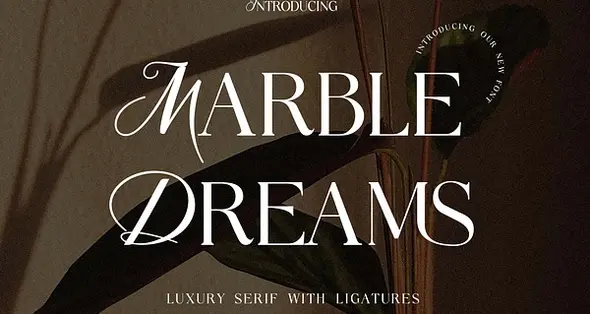
• Marble Dreams Luxury Serif Font
فونت انگلیسی مدرن لوکس
• circle سایز پیشنهادی: فشن، ژورنال، مجله
• circle سبک قلم: Serif
• circle لیگچر
«ماربل دریمز» یک فونت نمایشی مدرن است که حسی از زیبایی، کلاس، ظرافت و استایل منحصربه‌فرد را القا می‌کند. این فونت برای طیف گسترده‌ای از پروژه‌ها از جمله امضا، طراحی ست اداری، لوگو، مراسم عروسی، نقل‌قول‌های تایپوگرافی، جلد مجله یا کتاب و هدر وب‌سایت‌ها ایده‌آل است. طراحی این فونت به گونه‌ای است که در برندینگ‌های مربوط به مد یا طراحی‌های ادیتوریال جای می‌گیرد و هر دو ویژگی مردانه و زنانه را به نمایش می‌گذارد.
ویژگی‌های اصلی:
• دارای تعداد بسیار زیادی گلیف (Glyphs)
Marble Dreams Luxury Serif Font. The modern display font feels beautiful classy, elegant, and stylish. This font is ideally suited for a wide variety of projects, such as signature, stationery, logo, wedding, typography quotes, magazine or book covers, website headers, branding, and more. Also, fashion-related branding or editorial design displays both masculine and feminine qualities.